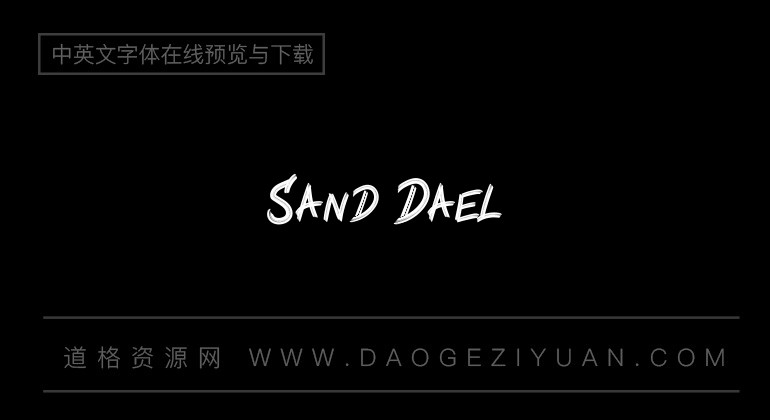
Sand Dael
Sand Dael 是一款简洁时尚的字体,它结合了现代技术和传统设计,具有良好的可读性和可视性。它可以用于各种不同的场合,比如商业广告、网页设计、印刷品、品牌标识等。它的字体特点是细节丰富,把细节和质感融合在一起,具有流动的线条和清晰的字母。
Sand Dael是一款非常不错的手写艺术字体,具有很好的视觉感,适合于文化类的宣传设计、商业类品牌的广告和产品包装设计以及个性化文字排版等较多场景。